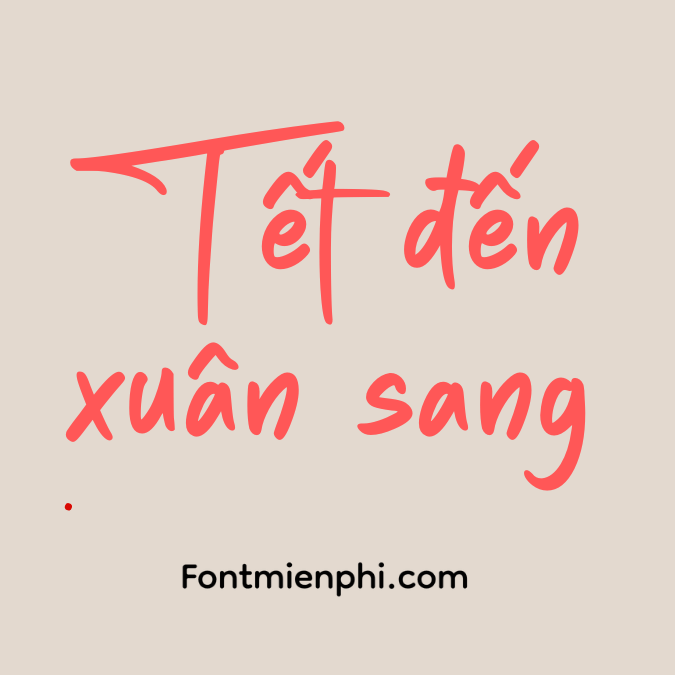
Font Việt hóa 1FTV VIP Paul Jackson ,Font tết
Font Việt hóa 1FTV VIP Paul Jackson
Font Việt hóa 1FTV VIP Paul Jackson là một kiểu chữ được thiết kế đặc biệt để hỗ trợ tiếng Việt, mang lại sự tiện lợi cho người sử dụng trong việc soạn thảo văn bản. Kiểu chữ này có phong cách hiện đại, rõ ràng và dễ đọc, phù hợp cho nhiều mục đích sử dụng như in ấn, thiết kế đồ họa, hay viết nội dung trên các nền tảng số.
Đặc điểm nổi bật của font này bao gồm:
• Hỗ trợ đầy đủ ký tự tiếng Việt: Bao gồm các dấu và ký tự đặc biệt, giúp người dùng dễ dàng viết đúng ngữ pháp và chính tả.
• Thiết kế tinh tế: Các chữ cái được thiết kế với độ dày và khoảng cách hợp lý, tạo cảm giác thoải mái khi đọc.
• Tính linh hoạt cao: Font này có thể được sử dụng trong nhiều bối cảnh khác nhau từ tài liệu chính thức đến thiết kế sáng tạo.
Với những ưu điểm trên, font Việt hóa 1FTV VIP Paul Jackson trở thành sự lựa chọn lý tưởng cho những ai cần một kiểu chữ đẹp và dễ sử dụng trong các sản phẩm văn bản tiếng Việt.
1FTV VIP Paul Jackson là một font chữ Viết tay phù hợp với các thiết kế Thiệp mời, thiết kế ấn phẩm quảng cáo tết và nhiều mục đích khác.